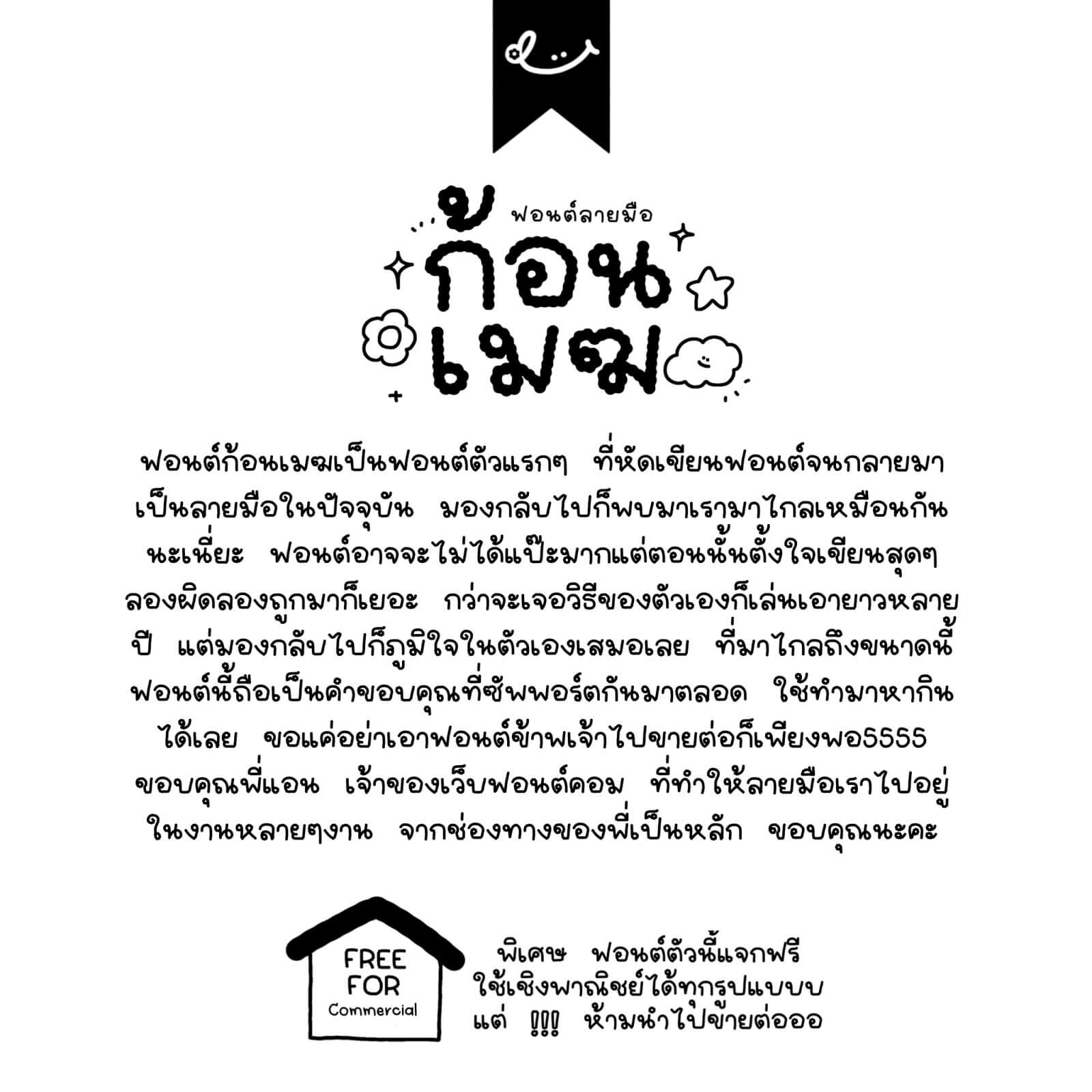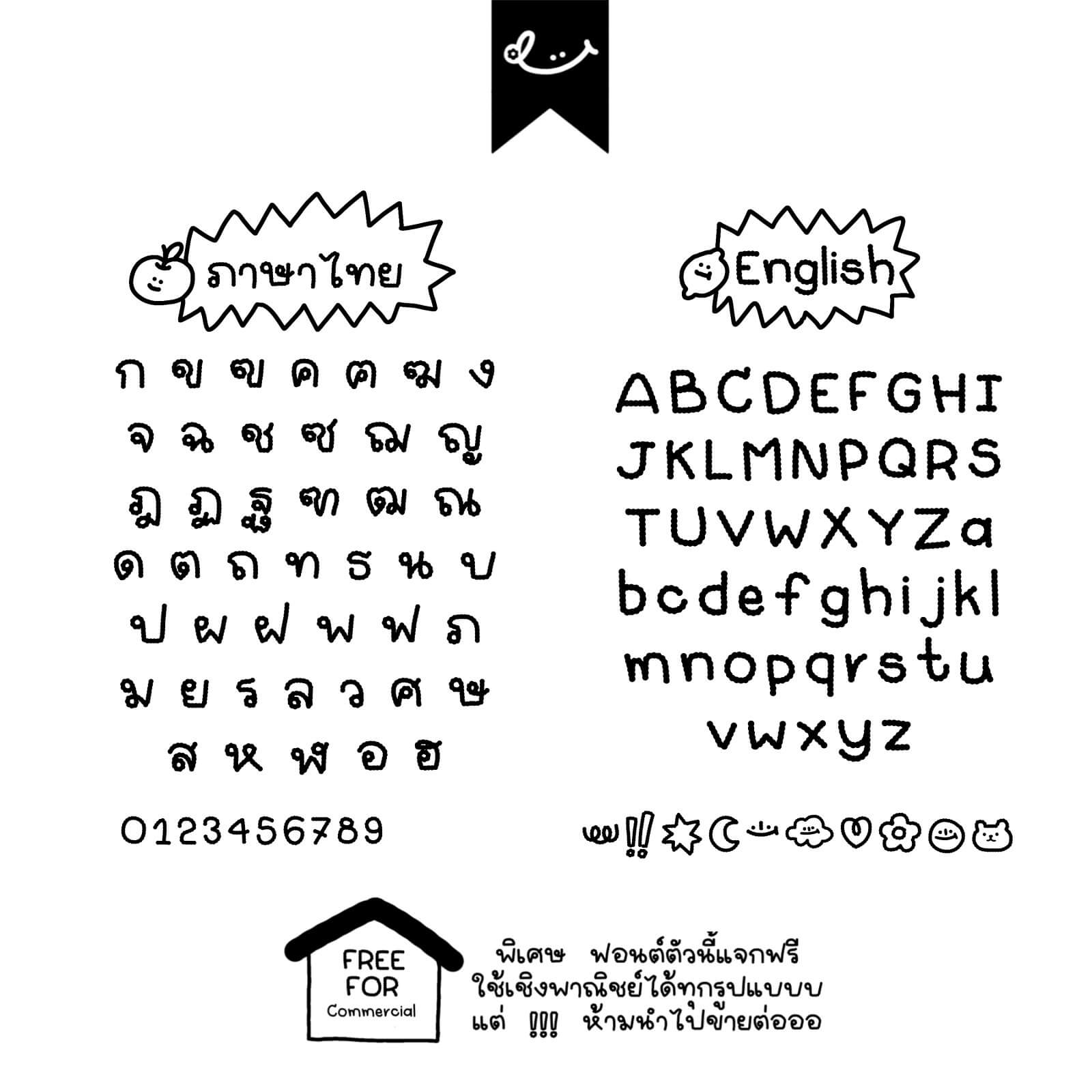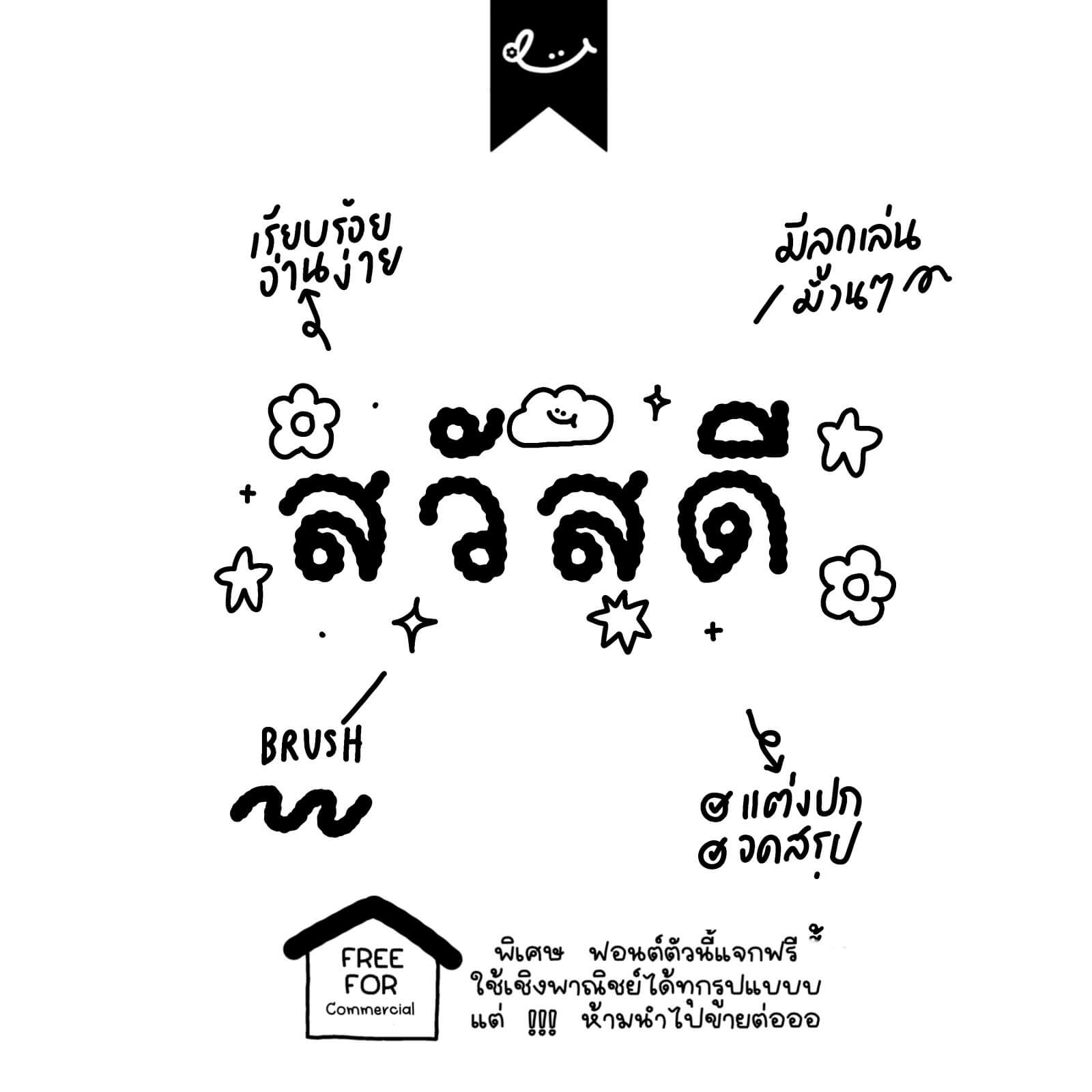
ก้อนเมฆ (RDKonmek)
ฟอนต์ก้อนเมฆเป็นฟอนต์ตัวแรกๆ ที่หัดเขียนฟอนต์จนกลายมาเป็นลายมือในปัจจุบัน มองกลับไปก็พบมาเรามาไกลเหมือนกันนะเนี่ย
ฟอนต์อาจจะไม่ได้เป๊ะมาก แต่ตอนนั้นตั้งใจเขียนสุดๆ ลองผิดลองถูกมาก็เยอะ กว่าจะเจอวิธีของตัวเองก็เล่นเอายาวหลายปี แต่มองกลับไปก็ภูมิใจในตัวเองเสมอเลย ที่มาไกลถึงขนาดนี้ ฟอนต์นี้ถือเป็นคำขอบคุณที่ซัพพอร์ตกันมาตลอด